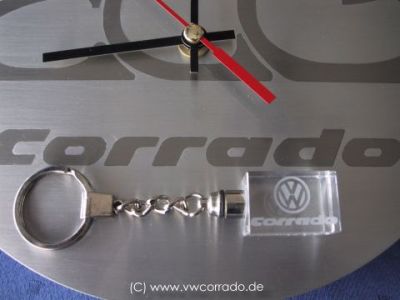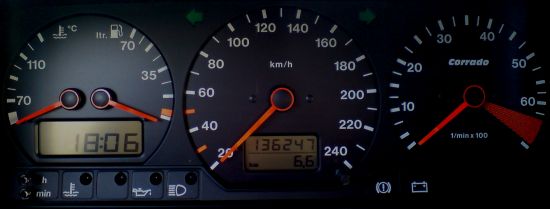
Tacho-Schrift VW-Corrado
Welche Schriftart ist das? Jemand eine Idee?
Die original VW Schrift isses leider nicht :(
die Zahlen scheinen auf den ersten Blick zu passen. Allerdings passt beim Wort Corrado das a nicht ;(
Ich versuche den Tacho nachzugestalten. Ich brauche nach Möglichkeit alle verwendeten Schriftarten.
Ist das der Corrado-Schriftzug?
gefunden auf http://www.vwcorrado.de/s17_corrado_accessoires.html ganz unten ...
und auf den Türen stehen dann im Fall immer die Initialen von Fahrer/Beifahrerin (da wollt ich jetzt wirklich was mit "schlafen" zusammenreimen ...) vorzugsweise in Englischer Schreibschrift und wenn der ganze Name, dann ausschließlich in Großbuchstaben der gleichen Type :twisted:
ich glaube das d passt nicht ganz bei Corrado mit Antique Olive Nord Italic :(
wenn du den schirftzug nachbauen musst dann digitalisier in doch
einfach. ist zwas mühsamer als absetzen aber immer noch schneller
als nach der passenden typo zu suchen ...
@Microboy
danke passt aufn ersten blick ganz gut.
zur Info:
Ich programmiere diesen Tacho in Flash nach.
Der original Tacho wird dann durch 2 TFT Bildschirme ersetzt. Dort wird dann der Flashfilm laufen der die Tachodaten wie beim original anzeigt.
Da ich ein Corradofan bin, lege ich großen wert darauf dass es originalgetreu aussieht.
Im Flash selber sieht eine Schriftart bei variablen größen wesentlich besser aus als ein Bild, weshalb ich die richtig Font suche.
Und warum das ganze?
Ganz einfach, ich habe so die Möglichkeit den Tacho nach meinen wünschen zu erweitern. Mp3 Player, Navi, Kameras, etc...
@mckoy